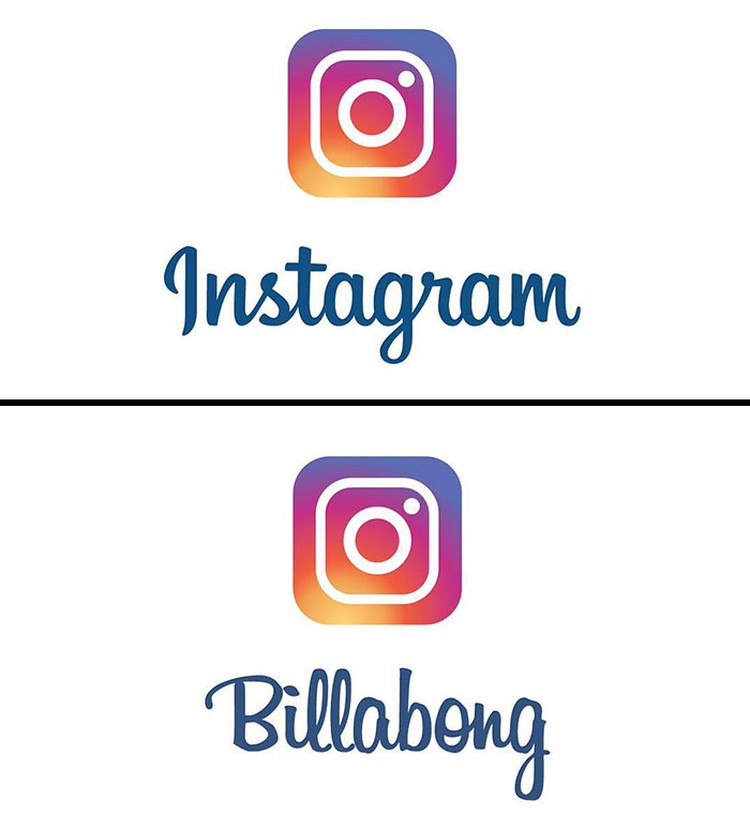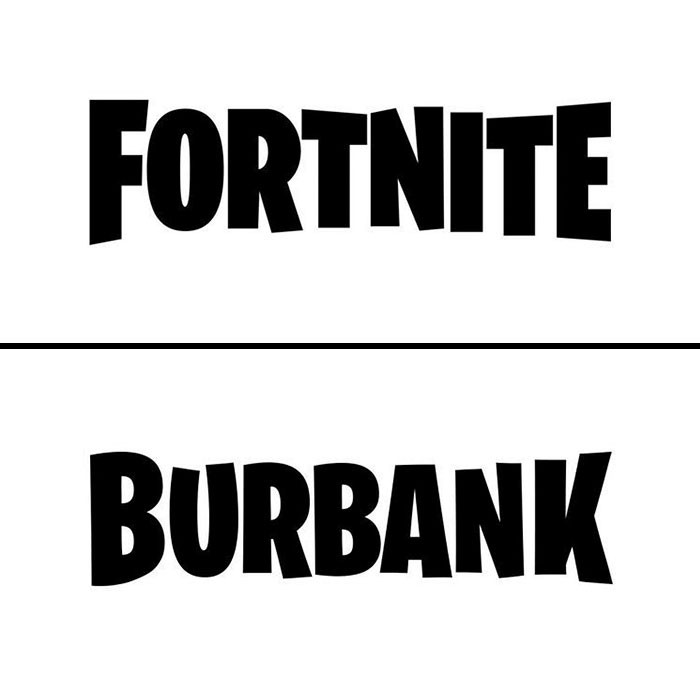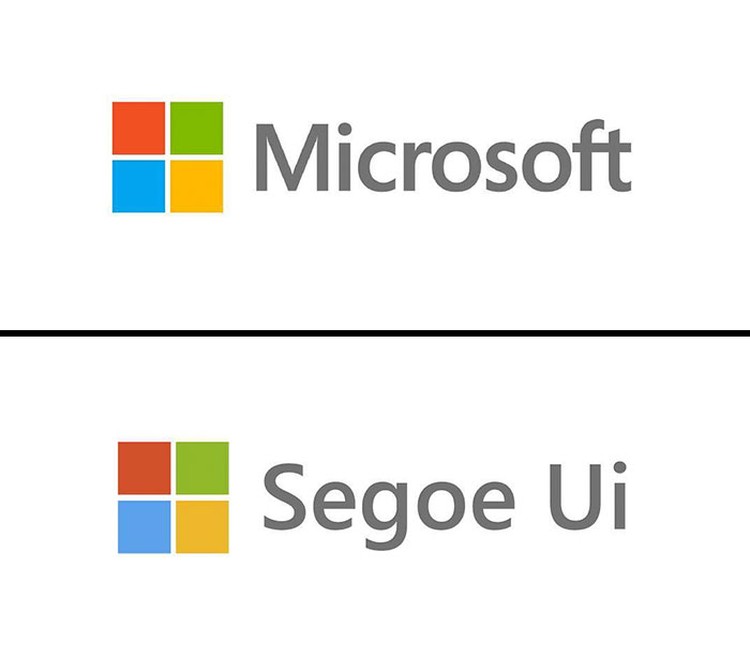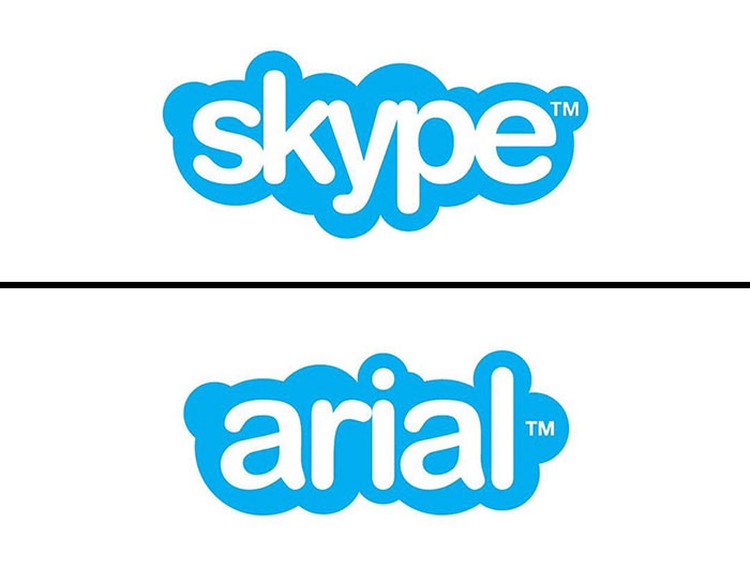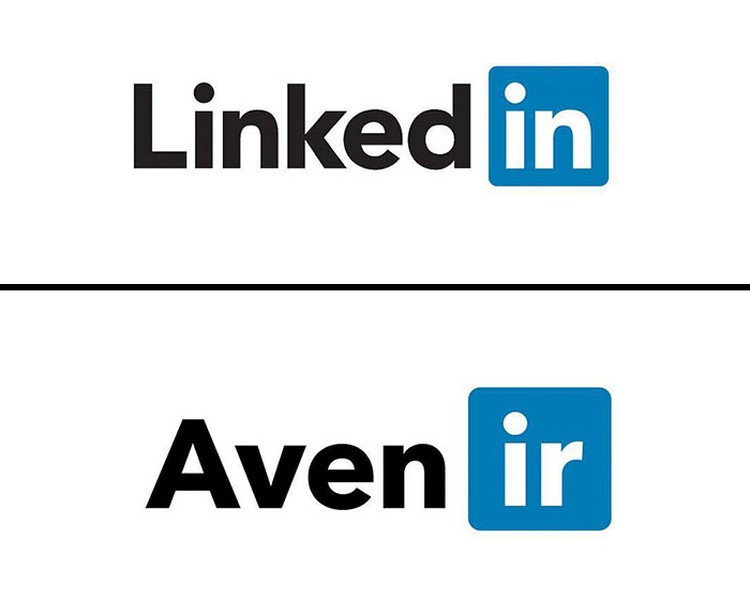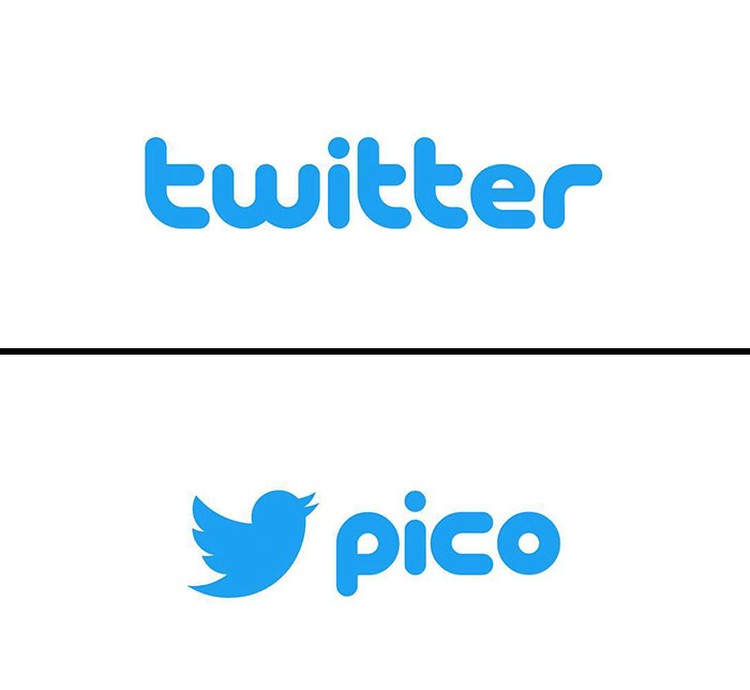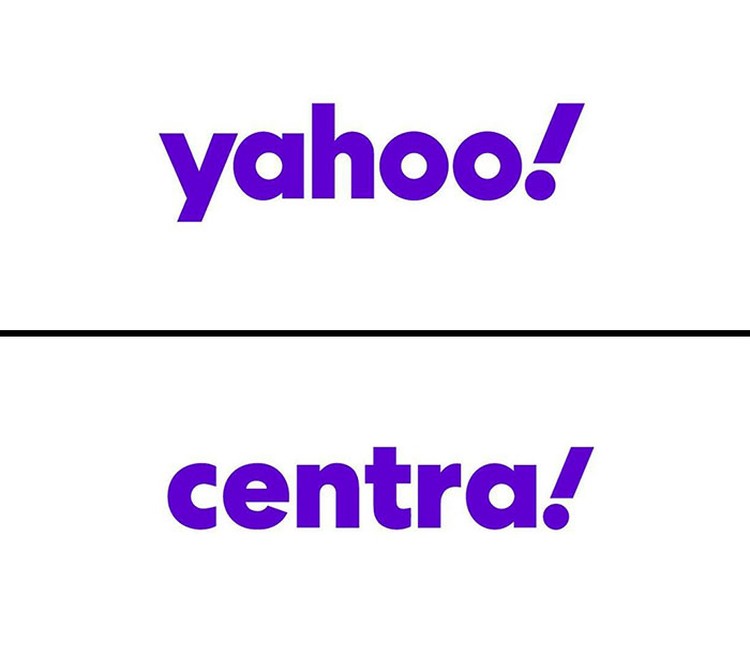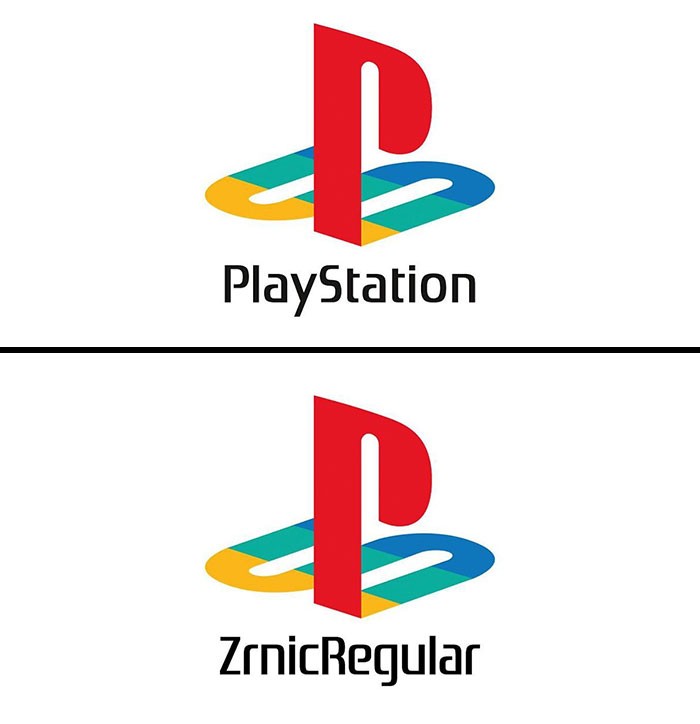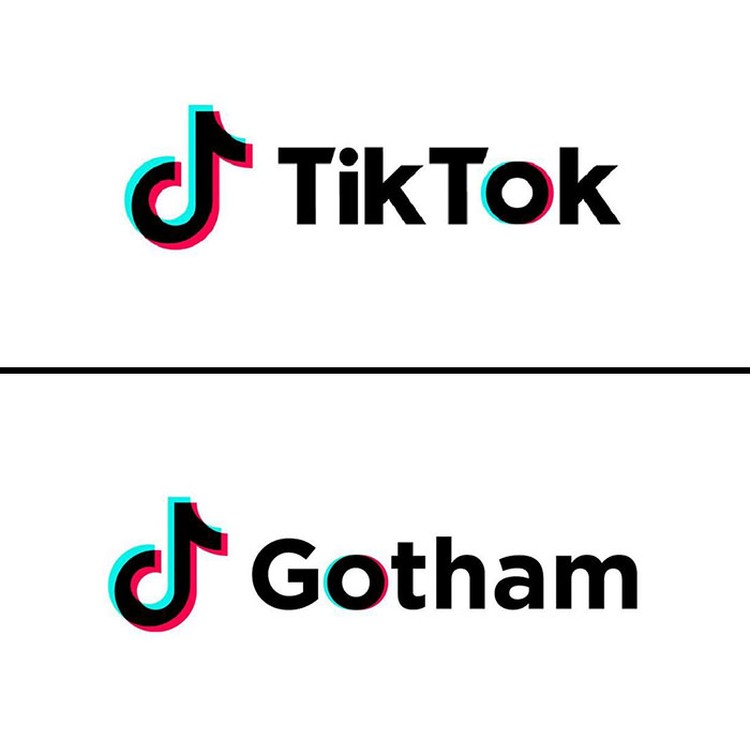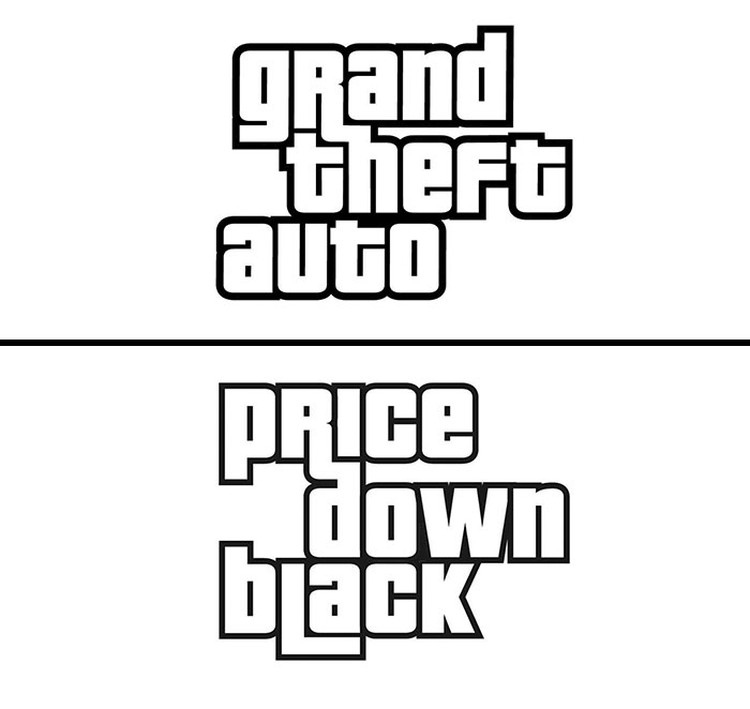
Deretan Fonts di Balik Logo Merek Populer
Jakarta - Semua perusahaan teknologi ternama memiliki logo dengan font yang menjadi ciri khasnya. Seorang desainer mengungkap font-font di balik logo populer.
Emanuele Abrate, seorang desainer grafis asal Italia mengungkap font yang digunakan perusahaan ternama untuk membuat logonya yang populer. Foto: Bored Panda/logo_fonts
Proyeknya itu diunggah lewat akun Instagram @logo_fonts. Saat ini ia sudah memiliki lebih dari 45 ribu followers. Foto: Bored Panda/logo_fonts
Kepada Bored Panda, Abrate mengatakan ide proyek ini datang dari pertanyaan banyak desainer grafis yang ingin mengetahui font di balik logo-logo populer. Foto: Bored Panda/logo_fonts
Abrate mengatakan sebagian besar logo terkenal memiliki tipografi khusus yang dikustomisasi. Foto: Bored Panda/logo_fonts
Entah logo itu dibuat sendiri dari awal atau menggunakan font yang sudah ada lalu dimodifikasi. Foto: Bored Panda/logo_fonts
Jadi ada beberapa logo yang memang tidak terlihat sama persis dengan font aslinya. Foto: Bored Panda/logo_fonts
"Tujuan saya adalah menemukan font apa yang digunakan di awal dan dimodifikasi untuk mendapatkan hasil akhirnya," kata Abrate. Foto: Bored Panda/logo_fonts
Untuk itu ia mencar informasi dari merek dan membandingkan font dengan logo. Ia juga sering menggunakan alat seperti 'whatthefont'. Foto: Bored Panda/logo_fonts
Tujuan utama Abrate melakukan proyek ini adalah untuk menunjukkan bagaimana pemilihan tipografi bisa menghasilkan logo yang khas dan mudah diingat. Foto: Bored Panda/logo_fonts
Selain membagikan font yang digunakan oleh merek-merek ternama, Abrate juga memanfaatkan akun Instagramnya untuk membagikan tips soal merancang logo. Foto: Bored Panda/logo_fonts
Untuk menampilkan kesan mewah dan mahal, Abrate mengusulkan untuk menggunakan font serif atau elegant script. Foto: Bored Panda/logo_fonts
Sedangkan untuk menampilkan inovasi dan kecanggihan, gunakan sans serif atau font yang alami. Foto: Bored Panda/logo_fonts
Abrate mengatakan ada satu kesalahan besar yang biasa dilakukan perusahaan saat membuat logo. Foto: Bored Panda/logo_fonts
Untuk membuat logo yang sesuai, perusahaan seharusnya tidak mengandalkan selera mereka atau selera konsumen. Foto: Bored Panda/logo_fonts
"Saya menyukai Futura, tapi ketika saya merancang, saya mengesampingkan selera pribadi untuk mengikuti konsep yang ingin saya kuatkan," kata Abrate. Foto: Bored Panda/logo_fonts